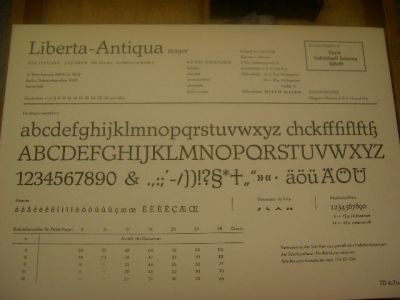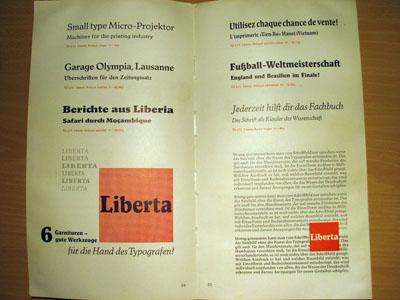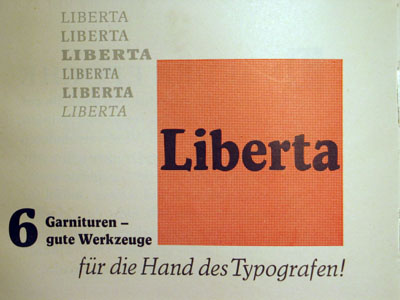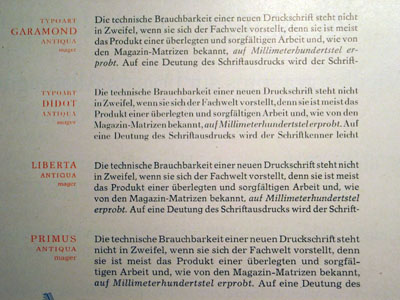
Liberta-Antiqua auf digitalem Schriftträger gesucht!
gibt es diese Schrift schon als Font, oder hat jemand ein gutes Schriftmuster oder einen Andruck?
Liberta-Antiqua, Herbert Thannhaeuser, Typoart 1956
glaube nicht - aber einen ähnlichen:
Dederon Serif is specifically designed for book setting. Design of this font started in 2004. Liberta font by East Germany type foundry TypoArt was an inspiration for design, especially its duct and width proportions. Eventually after careful evaluation of the pattern these are the only two elements left for inspiration and therefore Dederon is an original high-quality font project. Dederon Serif contains most of the characteristic components of dynamic antique such as inclined axis of shading, raised middle height, and smaller differences between main and secondary strokes. Typical drawing of types excels in bigger sizes - calligraphic principles specific for traditional Czech fonts of Oldřich Menhart such as extraordinary serifs hinting pen strokes, shape of stems or the endings of tails and ears.
Sans serif version of the font - Dederon Sans was created after final tuning of the serif face. It is based on the same drawing principles as antique giving the font open humanistic features and in the same time is sensitively subjected to the patterns of modern grotesque. It preserves the same duct coloring in individual weights, width proportions, middle height, overlapping length or italics inclination as serif version of the font.
Each Dederon Open Type Pro contains standard West European and Central European characters, wide range of basic and accented ligatures, genuine capitals, non-aligning, capital, small-capital, table, fractional and index numeral characters, expert glyphs and alternative variations, together more than 800 glyphs in one type face for comfortable work on the most demanding projects.
Ich habe DIN A5 quer Typo-Skizzenkarteien dieser Schrift in mager, halbfett, kursiv-mager, extrafett, schmalhalbfett, schmalfett. Auf Wunsch kann ich sie gern leihweise zum Scannen zur Verfügung stellen.
Das Erstguß-Jahr ist nach deren Angaben 1958, nicht, wie der werte Vorschreiber angibt, 1956. Aber das ist ja nur eine Marginalie.
Ich bin auf der Suche nach Scans (in guter Auflösung) der Liberta. So bin ich hier auf den alten Thread gestoßen. Habt ihr die Schriftmuster eventuell noch? Falls ja würde ich mich sehr darüber freuen! Leider finde ich nur relativ schlechte Bilder online.
Es geht vor allem um kleine Schriftgrößen. Dafür reicht die Auflösung der Online-Quellen leider oft nicht aus.
Was genau hast du denn mit den Scans vor? Wenn man es besser versteht, kann man vielleicht auch besser helfen.